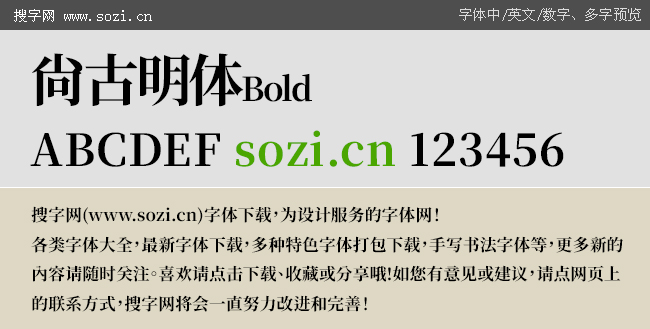
尚古明體Bold
搜字網(wǎng)提供一款尚古明體Bold中文字體下載,尚古字體是一套泛中日韓傳承字形(舊字形),基于思源黑體、思源宋體、思源等寬以及思源系列衍生字型制作,包含黑體、明體、圓體、等寬以及簡轉(zhuǎn)繁字型。這款字體無論是個人還是企業(yè)都可以自由免費商用,無需知會或者標明原作者。適合包裝設(shè)計、海報設(shè)計、廣告設(shè)計等應(yīng)用。